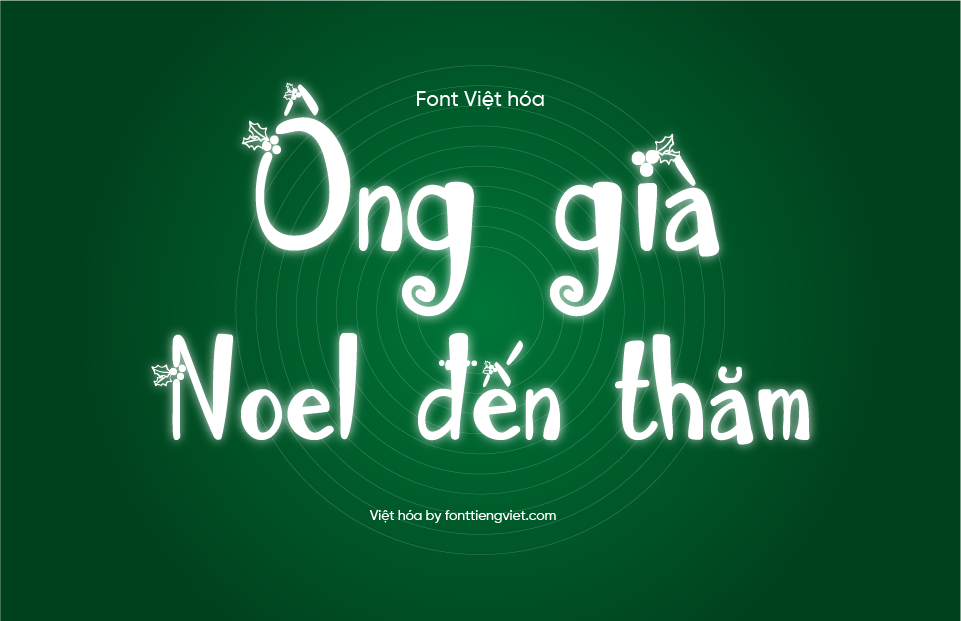
Font Việt hóa 1FTV Austie Bost Happy Holly – Giáng sinh là lựa chọn hoàn hảo cho các thiết kế Noel như thiệp chúc mừng, banner, poster, nhãn dán và bài đăng mạng xã hội. Font mang phong cách viết tay đáng yêu, bo tròn mềm mại, tạo cảm giác ấm áp và vui tươi. Bộ font đã Việt hóa giúp gõ tiếng Việt đẹp, hạn chế lỗi dấu khi thiết kế.
Giới thiệu Font Việt hóa 1FTV Austie Bost Happy Holly – Giáng sinh
Mùa Noel luôn là thời điểm “vàng” để thiết kế các ấn phẩm truyền thông: thiệp Giáng sinh, banner khuyến mãi, poster sự kiện, menu quán cà phê, nhãn sản phẩm mùa lễ hội… Và để thiết kế nổi bật hơn, việc chọn đúng font chữ theo chủ đề là cực kỳ quan trọng. Font Việt hóa 1FTV Austie Bost Happy Holly – Giáng sinh là một trong những font chữ mang vibe lễ hội rõ nét: vui tươi, ngọt ngào và dễ thương.
Điểm cộng lớn của font này là đã Việt hóa, giúp bạn gõ tiếng Việt mượt mà, dấu hiển thị ổn định hơn trong các phần mềm phổ biến như Photoshop, Illustrator, Canva hoặc các công cụ thiết kế online khác. Nếu bạn đang làm content thiết kế Noel, đây là “trợ thủ” rất đáng thử.
Đặc điểm nổi bật của Font Việt hóa 1FTV Austie Bost Happy Holly
• Phong cách viết tay đáng yêu: Nét chữ mềm, bo tròn, tạo cảm giác gần gũi – phù hợp không khí Giáng sinh.
• Trang trí tốt cho tiêu đề: Font nổi bật khi dùng làm headline, quote ngắn, tên chương trình hoặc call-to-action.
• Hỗ trợ tiếng Việt: Phiên bản Việt hóa giúp hiển thị dấu tốt hơn, giảm tình trạng lỗi font khi dàn trang.
• Hợp nhiều loại thiết kế Noel: Thiệp chúc mừng, sticker, banner sale, story Facebook/Instagram, thumbnail YouTube…
Ứng dụng gợi ý trong thiết kế Giáng sinh – Font Việt hóa 1FTV Austie Bost Happy Holly
Với kiểu chữ dễ thương và mang hơi hướng lễ hội, bạn có thể dùng 1FTV Austie Bost Happy Holly cho:
• Thiết kế thiệp Noel (Christmas Card) cho bạn bè, khách hàng
• Poster sự kiện, sân khấu mini, workshop mùa lễ hội
• Banner khuyến mãi “Merry Christmas Sale”, “Year End Sale”
• Nhãn sản phẩm, tag treo, bao bì quà tặng
• Ảnh quote Noel, template story và bài đăng social
Mẹo dùng font đẹp hơn (không bị rối)
Để font phát huy đúng “chất Noel”, bạn nên:
• Dùng cho tiêu đề hoặc cụm chữ ngắn; phần nội dung dài nên kết hợp với sans-serif dễ đọc.
• Chọn tone màu Noel: đỏ, xanh lá, trắng, vàng kim để đúng không khí lễ hội.
• Kết hợp thêm icon tuyết, chuông, cây thông, hộp quà để bố cục sinh động hơn.